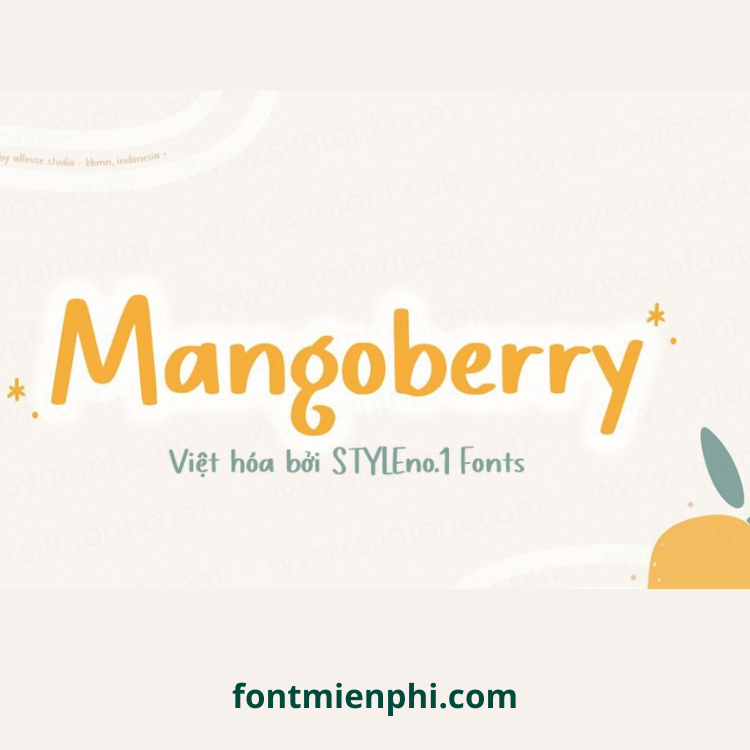
Việt hóa font SVN Mangoberry
Việt hóa font SVN Mangoberry – Font SVN Mangoberry Việt hóa là phiên bản hỗ trợ tiếng Việt của font chữ SVN Mangoberry, mang phong cách handwritten dễ thương, nét mềm mại và ngẫu hứng. Font phù hợp cho các thiết kế cần sự tươi vui, trẻ trung như poster, card, logo, bao bì, hoặc nội dung digital (social media, blog).
Gợi ý ứng dụng:
- Thiết kế logo quán café, bánh ngọt
- Tạo sticker, bao bì sản phẩm
- Làm poster event, thiệp mời
- Chữ nghệ thuật trên Canva, Photoshop
Font có độ đậm vừa phải, dễ đọc, đi kèm bộ ký tự tiếng Việt đầy đủ (Unicode).